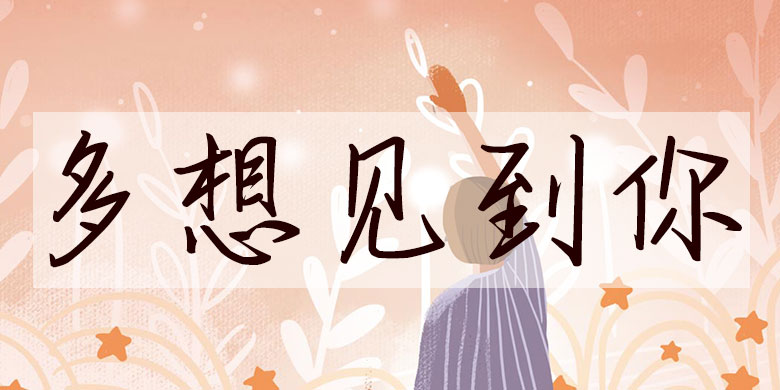
方正手迹-多想见到你字体说明方正手迹-多想见到你字体英文名称:FZSJ-DUOXJDN.TTF方正手迹-多想见到你品牌:方正手迹 设计师: 余丹发行时间:2019字库编码: 大陆简体(GB2312-80)分类: 常规书写·硬笔字体属性: 心动字字体介绍字形修长,骨骼清秀俊雅。行笔节奏有徐有急,具有质朴清新的手写特点。字笔锋纤细凌厉,点划粗细错落有致。适用于文艺类的书刊、品牌广告和产品包装设计,以及社交网络的个性化用字。字体下载地址官网下载 发布日期 2020年7月20日 发布于 方正字体 标签 GB2312-80, pop, 心动字, 手写, 方正, 方正手迹, 粗, 细 上篇文章: 方正手迹-霸道傲娇-狮子座 下篇文章: 方正手迹-把孤单当做晚餐 发表回复 取消回复要发表评论,您必须先登录。